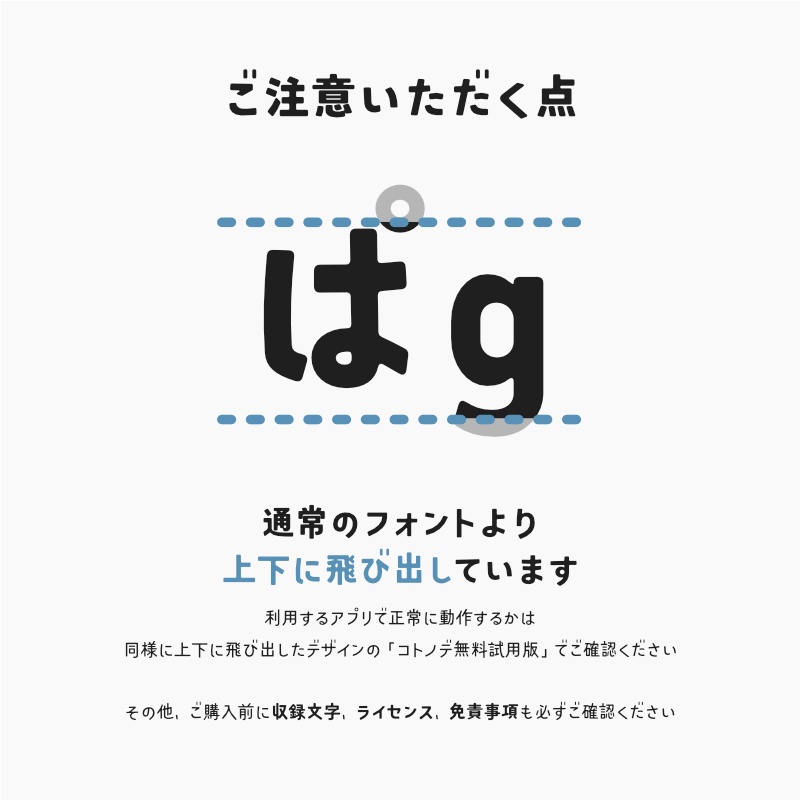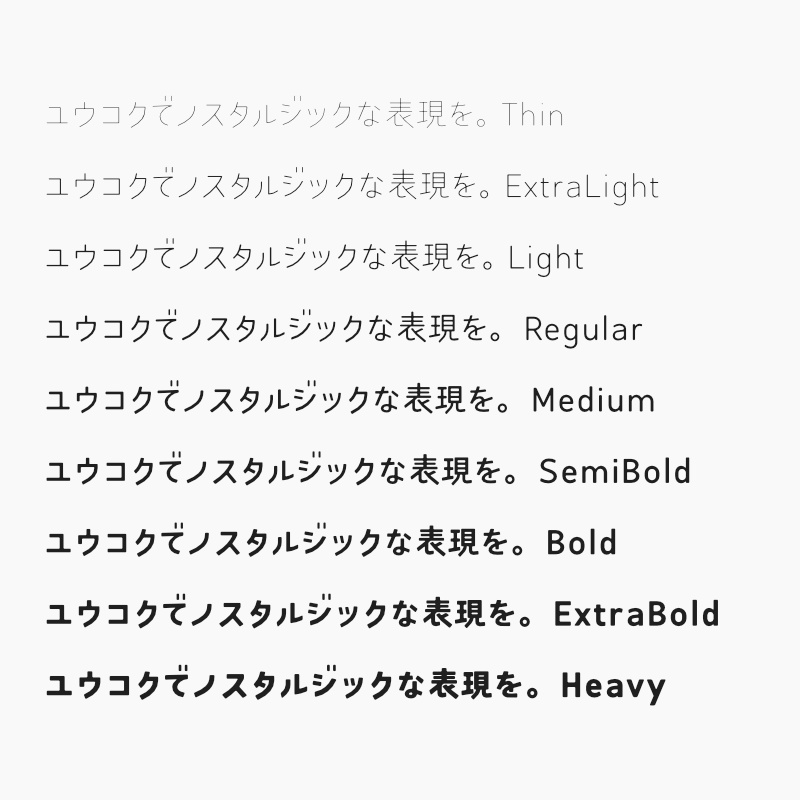
「ユウコク」フォント(漢字あり) ~おしゃれでノスタルジックなゴシック体~
・通常のフォントよりも上下にはみ出たデザインです。ご利用のアプリによっては上下が見切れることがあります。ご購入前に確認したい場合は、同様に上下にはみ出たデザインの「コトノデ無料試用版(※)」をご活用ください。 ・漢字は6,700文字以上収録しており、常用漢字・JIS第一水準漢字・JIS第二水準漢字をカバーしています。収録文字は公式の紹介ページをご確認ください。 ・公式の紹介ページの利用規約・免責事項を必ず確認してください(商用利用可・再配布禁止)。 【公式の紹介ページ】 https://kotonohaworks.com/yukoku.html (※コトノデ無料試用版) https://dkf.booth.pm/items/2727320(無料試用版に漢字は含まれていません。) ■アップデート履歴 2025/06/11 ver.1.001 リリース。 2025/09/08 ver.1.002 リリース。一部ひらがなのデザインを微調整しました。「以」「似」などを画数に忠実なデザインに変更しました。「篝」をJIS2004字形に変更しました。 ※購入済み商品の最新版は、「購入履歴」「ライブラリ」ページからダウンロードできます。